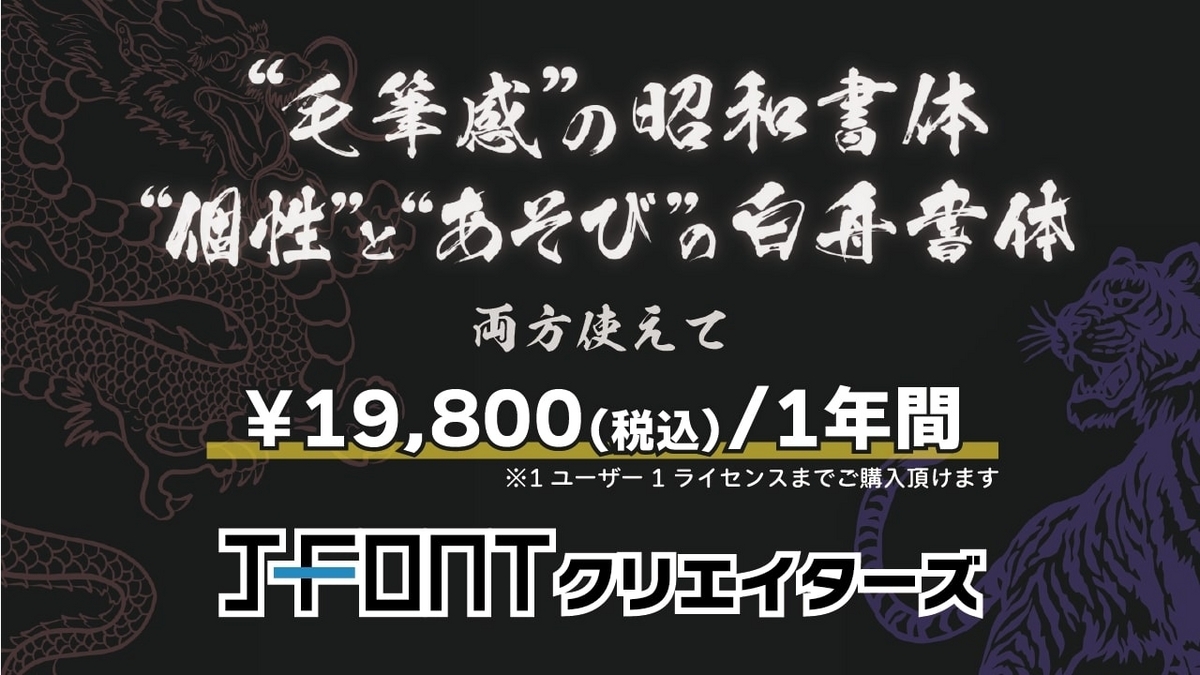
最強の筆文字プラットフォームJ-Font.comからクリエイター必見となる白舟×昭和による超特価プラン「J-Fontクリエイターズ」爆誕!!
アナログとデジタルの両面から企業の持続的成長を支援する「ハイブリッドDX」カンパニーのシヤチハタは、フォントサービス事業「J-Font.com(ジェイフォントドットコム)」にて、2023年5月10日(水)より昭和書体のフォントを提供開始することを2023年4月10日のフォントの日に発表した。
「J-Font.com」は、広告媒体やメディア、プロモーション活動や書籍、デジタルコンテンツなどに幅広く使えるフォントを提供するフォントサービス事業。
標準フォントとは一味違う迫力ある筆文字フォントに特化することで、「筆文字=J-Font.com」を目標にサービスを強化してきたが、好評リリース中の「白舟書体」筆文字フォントに「昭和書体」の筆文字フォント72書体の提供も開始された。
▼書体見本(一部)